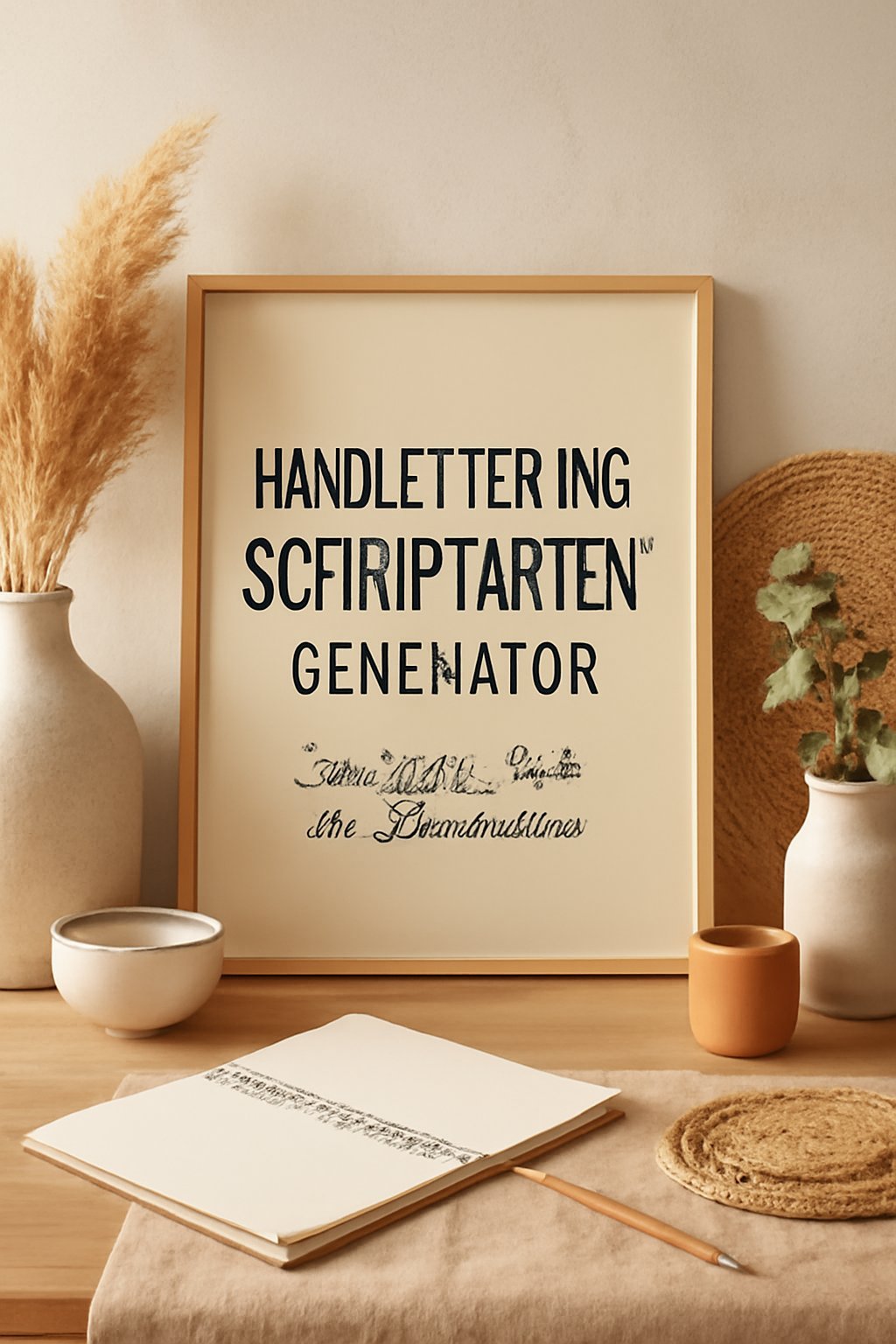
Warum Handlettering Schriftarten Generator
Handlettering Schriftarten Generator sind ein kreatives Werkzeug, das dir hilft, die kunstvolle Welt des Handletterings zu entdecken. Diese Technik hat ihren Ursprung in der Kalligrafie und erfreut sich seit einigen Jahren großer Beliebtheit. Egal, ob du dich für moderne Schriftarten oder klassische Stile interessierst, diese Generatoren bieten eine Vielfalt an Möglichkeiten, um deine persönliche Note in jede Deko zu integrieren und einzigartige Kunstwerke zu erschaffen. In den letzten Jahren haben viele Nutzer diese Generatoren für eigene Projekte wie Einladungen, Wandkunst oder Geschenkverpackungen entdeckt. Ein Handlettering Schriftarten Generator ermöglicht es dir, verschiedene Stile auszuprobieren, ohne die aufwendigen Techniken der traditionellen Kalligrafie erlernen zu müssen. Dadurch kannst du spielerisch experimentieren und findest schnell heraus, welcher Stil am besten zu dir und deinem Wohnraum passt. Dabei ist es wichtig, auf die Lesbarkeit der Schrift zu achten, vor allem, wenn du sie für dekorative Zwecke verwenden möchtest. Ein Generator, der dir verschiedene Varianten und Anpassungsoptionen bietet, wird dir dabei helfen, die perfekte Schriftart für dein Projekt zu finden. Zusammengefasst bieten Handlettering Schriftarten Generator nicht nur eine spannende Möglichkeit, deine Kreativität auszuleben, sondern auch den Vorteil, etwas Einzigartiges zu schaffen. Mit der richtigen Schriftart kannst du deinem Zuhause eine persönliche Note verleihen und selbst einfache Deko-Elemente in kleine Kunstwerke verwandeln.Handlettering Schriftarten Generator: 12 kreative Ideen zum Selbermachen
- Wähle ein Skizzenbuch aus und öffne die erste Seite. Nimm einen Bleistift und skizziere grob den Text, den du gestalten möchtest.
- Nimm das Lineal und zeichne leicht mit dem Bleistift Hilfslinien auf die Seite. Diese Linien helfen dir dabei, die Buchstaben gleichmäßig und in der richtigen Höhe zu gestalten.
- Jetzt kommt der kreative Teil: Nimm den Pinsel und die Tinte. Tauche den Pinsel in die Tinte und beginne, die Buchstaben nach deiner Skizze nachzuziehen.
- Wenn die erste Schicht trocken ist, kannst du mit einem Marker oder einem anderen Pinsel Akzente setzen. Gehe über die Buchstaben, um Schatten oder Umrisse hinzuzufügen.
- Lass den Schriftzug vollständig trocknen, bevor du die Skizze mit dem Radiergummi vorsichtig entfernst.
- Du kannst auch verschiedene Materialien ausprobieren, wie z.B. Aquarellfarben oder spezielle Kalligrafie-Stifte, um verschiedene Effekte zu erzielen.
- Denk daran, dass Übung den Meister macht. Je mehr du übst, desto besser wirst du darin, deine eigenen Schriftarten zu kreieren.
- Um deine Schriftzüge zu schützen, kannst du sie mit einem Fixativ besprühen oder in einem Rahmen präsentieren. So bleiben deine Kunstwerke lange schön und können bewundert werden.
Gelingtipps
- Übe regelmäßig, um deine Fähigkeiten im Handlettering zu verbessern und deinen eigenen Stil zu finden.
- Experimentiere mit verschiedenen Materialien, um herauszufinden, was dir am besten gefällt.
- Schau dir Tutorials an, um neue Techniken und Ideen zu entdecken.
- Halte die Tinte immer frisch, um ein gleichmäßiges Ergebnis zu erzielen.
- Achte darauf, die richtige Pinseltechnik anzuwenden, um saubere Linien zu ziehen.
Aufbewahrung & Haltbarkeit
Bewahre deine Handlettering-Projekte an einem trockenen Ort auf, um sie vor Feuchtigkeit zu schützen. Wenn du Tinte verwendet hast, stelle sicher, dass sie gut getrocknet ist, bevor du sie lagerst. Eingefroren werden sie nicht empfohlen, da die Materialien beschädigt werden können.
Variationsideen
- Kalligrafie: Verwende spezielle Kalligrafie-Stifte für einen klassischen Look.
- Aquarell: Füge Aquarellfarben hinzu, um einen sanften Farbverlauf zu erzielen.
- Digital: Nutze digitale Tools, um deine Schriftarten am Computer zu gestalten.
Schritt 1
Wähle ein Skizzenbuch aus und öffne die erste Seite. Nimm einen Bleistift und skizziere grob den Text, den du gestalten möchtest. Achte darauf, dass die Buchstaben gleichmäßig verteilt sind. Das gibt dir eine Vorstellung davon, wie der finale Schriftzug aussehen wird. Halte die Skizze leicht, damit sie später nicht durch die Tinte sichtbar ist.
Schritt 2
Nimm das Lineal und zeichne leicht mit dem Bleistift Hilfslinien auf die Seite. Diese Linien helfen dir dabei, die Buchstaben gleichmäßig und in der richtigen Höhe zu gestalten. Du kannst horizontale und vertikale Linien verwenden, um ein Raster zu erstellen. So wird dein Schriftzug ordentlich und professionell aussehen.
Schritt 3
Jetzt kommt der kreative Teil: Nimm den Pinsel und die Tinte. Tauche den Pinsel in die Tinte und beginne, die Buchstaben nach deiner Skizze nachzuziehen. Achte darauf, dass du die Tinte gleichmäßig aufträgst und die Pinselstriche kontrollierst. Lass die Tinte etwas trocknen, bevor du weiterarbeitest, um ein Verwischen zu vermeiden.
Schritt 4
Wenn die erste Schicht trocken ist, kannst du mit einem Marker oder einem anderen Pinsel Akzente setzen. Gehe über die Buchstaben, um Schatten oder Umrisse hinzuzufügen. Das gibt deinem Schriftzug mehr Tiefe und Charakter. Experimentiere mit verschiedenen Techniken und finde deinen eigenen Stil.
Schritt 5
Lass den Schriftzug vollständig trocknen, bevor du die Skizze mit dem Radiergummi vorsichtig entfernst. Überprüfe, ob alles gut aussieht und ob du vielleicht noch kleine Anpassungen vornehmen möchtest. Wenn du zufrieden bist, kannst du den Schriftzug in dein Zuhause integrieren oder verschenken.
Schritt 6
Du kannst auch verschiedene Materialien ausprobieren, wie z.B. Aquarellfarben oder spezielle Kalligrafie-Stifte, um verschiedene Effekte zu erzielen. Probiere aus, was dir am besten gefällt und entwickle deinen persönlichen Stil weiter. Das Handlettering ist ein kreativer Prozess, der viel Spaß macht und dir erlaubt, deiner Fantasie freien Lauf zu lassen.
Schritt 7